先日、ラジオで「あなたは幽霊を見たことがありますか」という話をしていました。幽霊って本当に存在するのか、はたまたただの妄想なのか分かりませんが、私もいくつか心霊話のネタを持っています。ちょっと、ここには書けませんが←
というわけで、今回はホラー系、怖いイメージのフォントをご紹介したいと思います。
ナイス、ホラー!難しい漢字や縦書きまで表すことが可能です。
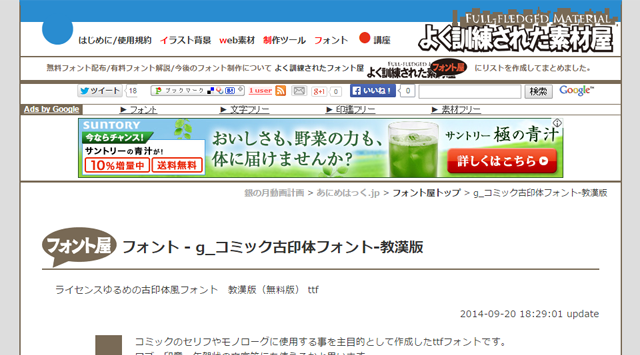
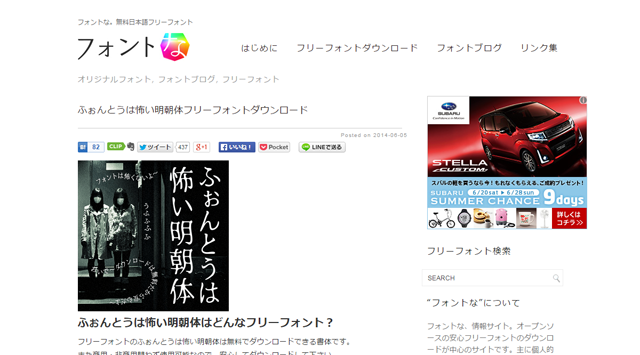
ゆらゆらと柔らかな明朝体のフォントです。確かに怖く見えます。
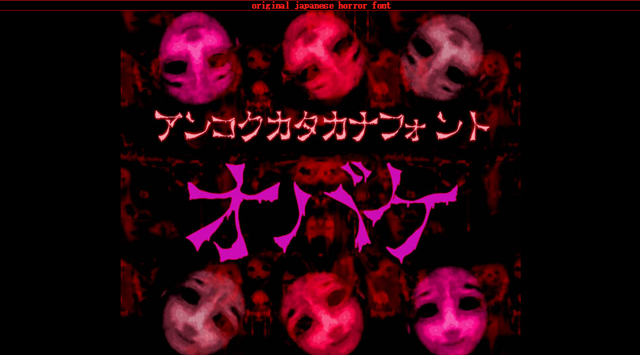
カタカナだけの文章というのも怖いかも知れませんね。
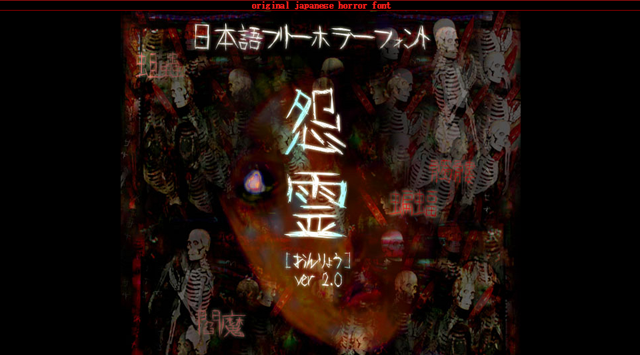
日本語のホラー系フォントといえば有名どころです。
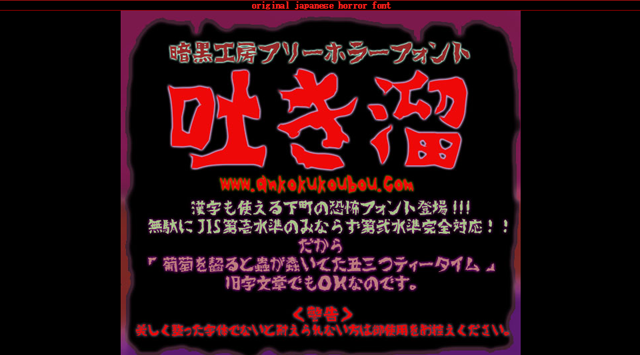
これもいい感じですね!太めなフォントです。
紙をカッティングしたようなフォントです。ハサミを持ってる幽霊、、、。ゲーム、クロックタワーの恐怖がよみがえる。
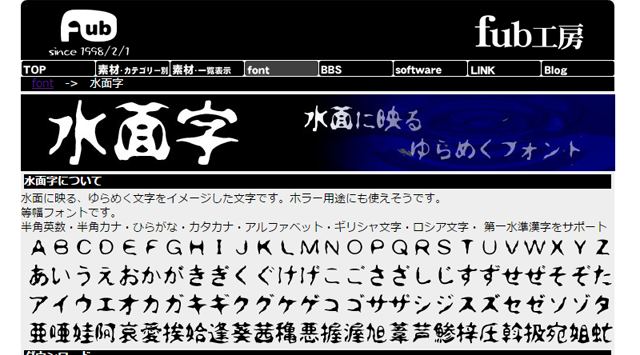
ゆらゆら系なので日本の幽霊イメージですね。
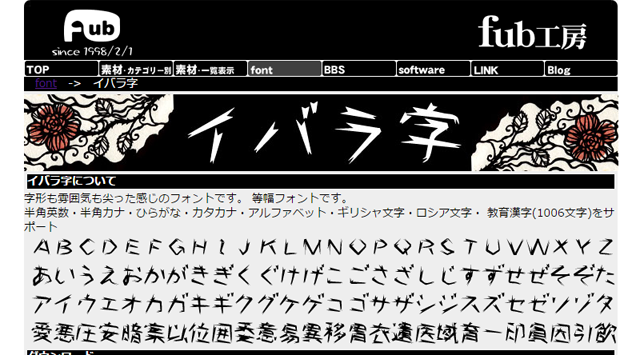
尖ってる!怨霊フォントをトゲトゲにしたイメージでしょうか。
実は本来違った印象を与えるフォントでもホラーな演出が出来るんです。以下のようなフォントでホラー感が出せます。
以上、ホラーなフォントをご紹介しました。今回はタイトル画像に、怨霊フォント、写真は暗い緑系に加工をしてホラー感を出してみました(*´∀`*)ふふ←